适合制作条幅的字体有哪些?条幅设计常用字体分享
在制作条幅时,字体的选择直接影响信息传达的清晰度与视觉感染力。无论是促销横幅、开业庆典条幅,还是会议指引,合适的字体能在远距离保持可读性,同时传递品牌或活动的气质。但初次设计条幅时,你是不是在犹豫该选用什么字体更合适?下面就来和本文一起来了解这 8 款适合条幅制作的字体素材,并从中挑选出自己喜欢的字体吧!
1、思源黑体
思源黑体笔画饱满、字形开阔,字距设计较为均衡,放大到条幅尺寸仍保持清晰不模糊。作为一款中性偏现代的无衬线字体,它的线条对比不强,视觉识别效率高。特别适合商品促销、大型导视和活动条幅,配色上建议使用高对比色,比如白字配深色底或黑字配浅色底。如果是在PPT或矢量软件中使用的话,建议将文字转为轮廓输出,这样可以避免位图拉伸失真。
2、思源宋体
思源宋体带有衬线特征,笔画末端有细微修饰,在条幅上能传达更正式或传统的气质。其字形结构稳重,适合用于欢迎词、典礼条幅或需要体现正规感的场合。因为它的衬线在远距离可能显得细弱,制作时可适度加粗或选择较大字号,确保远距离衬线不会导致识别干扰。这款字由在【字由】站内同样提供,还有更多适合制作条幅的字体素材,均可以前往字由站内搜索使用。
3、站酷酷黑体
站酷酷黑体风格偏圆润且具有现代感,笔画粗细适中,在线条端点处理上更显亲切,不会给人过于严肃的感觉。对比度高、识别度强,适合活动推广类条幅,尤其是面向年轻受众的场合。它在色彩鲜明的背景上表现良好,可作为主标题使用,与简洁的副文字搭配更有层次。实际使用时,可将标题适当加粗以增强远视可读性。
4、造字工房悦黑体
悦黑体笔画饱满且骨感好,字形经过细致优化,横竖笔画的粗细比例在大尺寸下仍然均衡。它在空白处理和字间距上表现不错,能够保证条幅上长句子也不显拥挤。它比较适合品牌条幅、企业形象类横幅,应用时可结合加粗或变体来强调核心信息。在导出用于印刷前,建议检查字距与行距在实际尺寸下的视觉效果。
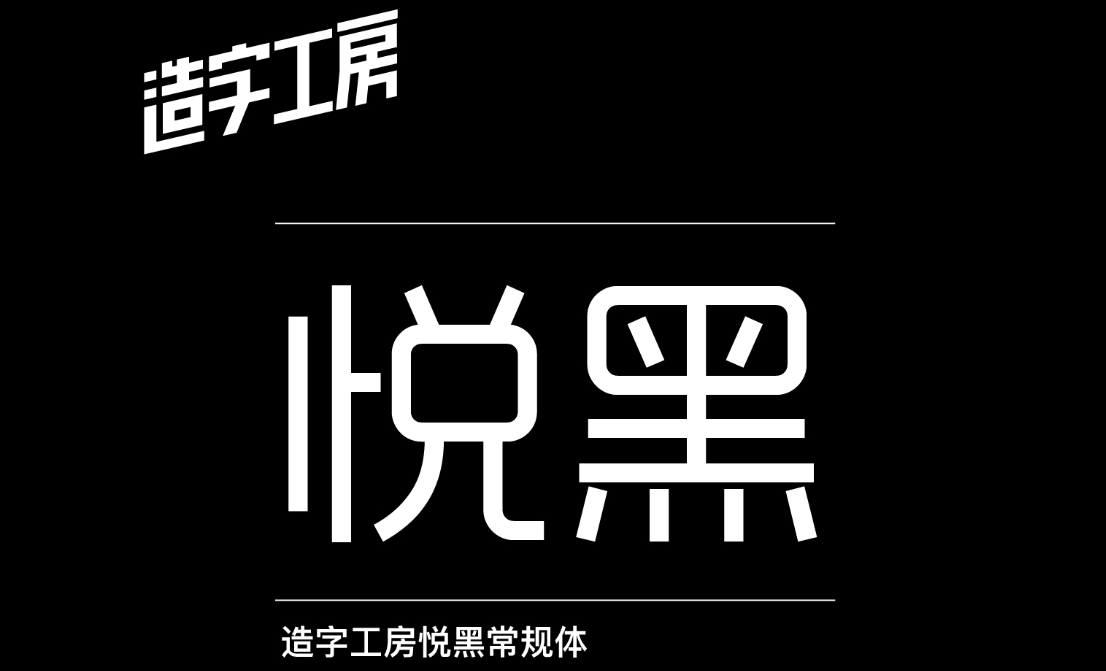
5、方正兰亭黑
兰亭黑线条干净利落,文字轮廓稳健,阅读效率高,是很多出版和视觉设计中常用的黑体款式。放大后不失真,视觉穿透力强,适合需要从较远距离传达信息的场景。如果要用于户外大型条幅或舞台背景,配色上注意避免过低的对比度以免影响可读性。若条幅信息较长,可使用更宽松的行间和字间设置来提升舒适度。
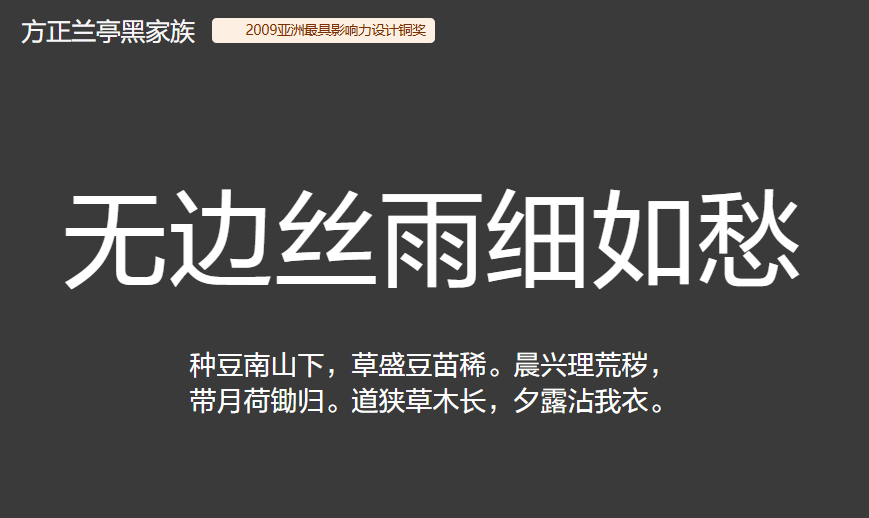
6、汉仪旗黑
汉仪旗黑保留了传统黑体的力度同时在字形细节上做了现代化处理,看起来沉稳而有力量。它在横向笔画的收尾上更为干净,条幅标题使用能起到提气势的作用。当要用于企业庆典或品牌发布等需要显现专业度的条幅。制作时可在设计稿中预览不同距视角的可读性,并根据观看距离调整字重。
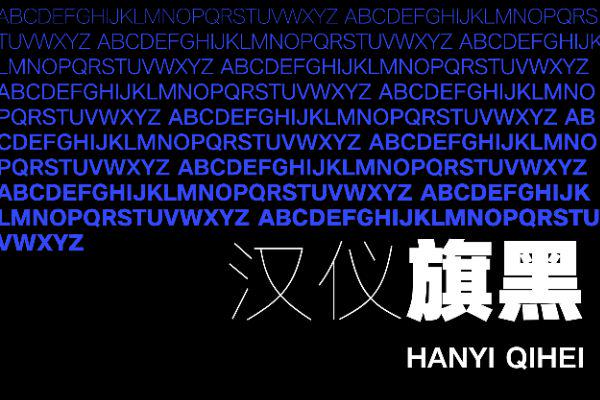
7、文泉驿正黑
文泉驿正黑为开源字体,字体结构简洁、笔画端正,适合用于信息量较大的条幅,如指引类或展会布局图上的标题与要点。可以在内部材料或非商业用途的条幅应用时考虑此字体,若用于商业发布则需确认授权与合规。由于它兼容性高,常用于快速排版与多平台预览。
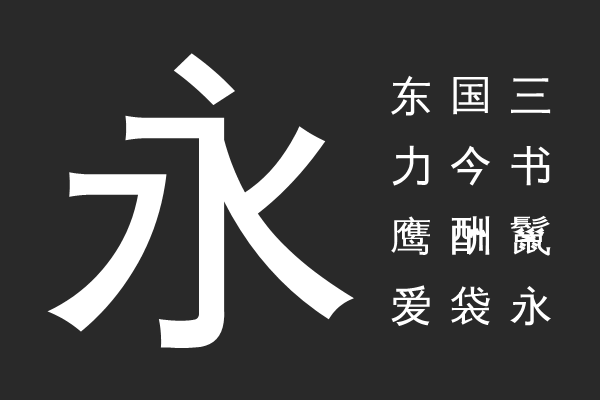
8、华文细黑
华文细黑属于系统常见字体,易于在各类办公软件中调用,兼容性高。其字形偏窄,放在横幅上显得利落,适合短字数的口号或主题词。在PPT中制作条幅预览时可优先用系统字体快速排版,最终成品建议替换为华文细黑并导出矢量以保证印刷质量。华文细黑便于团队协作和快速修订,但印刷前应做一次版权与效果确认。
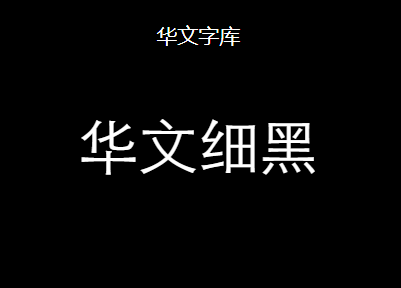
条幅设计的要点在于文字可读性,风格设计与技术输出这三者之间的平衡。从中性耐看的无衬线字体再到具有情感的衬线字体以及观感不同的黑体,本文推荐的这 8 款字体覆盖了大部分的条幅使用场景,可以满足你对条幅设计的字体需要。为了保证最终的条幅设计效果,在实际操作时,我们可以先在设计软件中使用真实尺寸进行预览测试,再输出矢量稿件。这样既能保证最终的视觉效果,也便于管理。